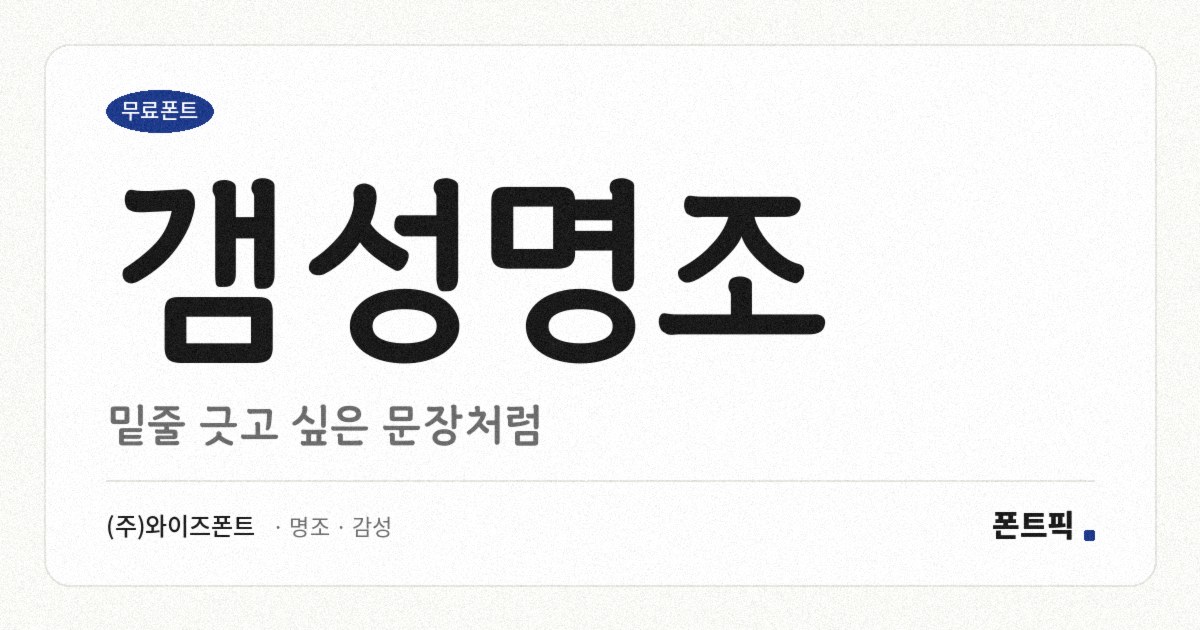
갬성명조
이름을 먼저 짚고 넘어가야 하는 서체입니다. 명조라는 이름이 붙어 있지만 파일을 열어 보면 획 끝에 부리가 없습니다. 세로획이 가로획보다 3할쯤 굵어 약간의 대비는 있지만, 전형적인 명조가 보이는 1.7배 이상의 대비에는 크게 못 미칩니다. 부리 없는 민부리에 굵기 변화를 살짝 준 형태에 가깝습니다.
그래서 인상은 명조의 격식보다 손글씨의 부드러움 쪽입니다. 받침이 붙어도 높이가 거의 변하지 않는 네모틀이고 낱자는 정사각형에 가까워, 손글씨 계열치고는 글줄이 가지런하게 떨어집니다.
명조를 찾다가 이 서체를 고르시는 거라면 기대와 다를 수 있습니다. 반대로 부드럽고 감성적인 인상의 서체를 찾는 자리라면 잘 맞습니다. 현대 한글 11,172자를 모두 담았고 굵기는 하나입니다.